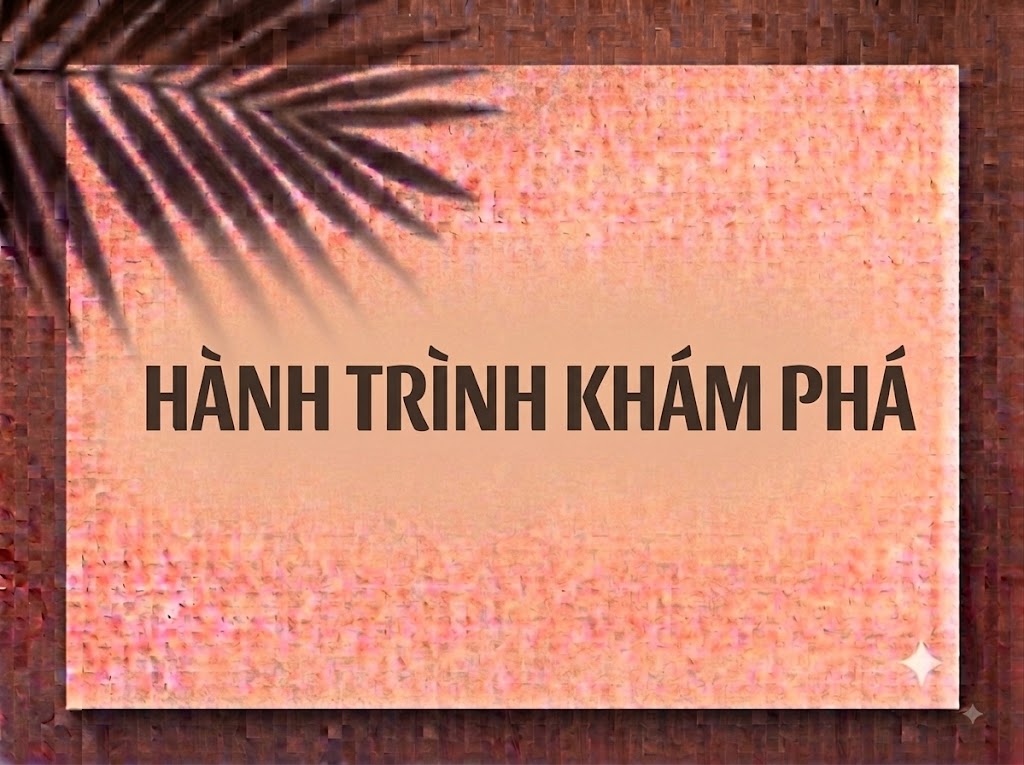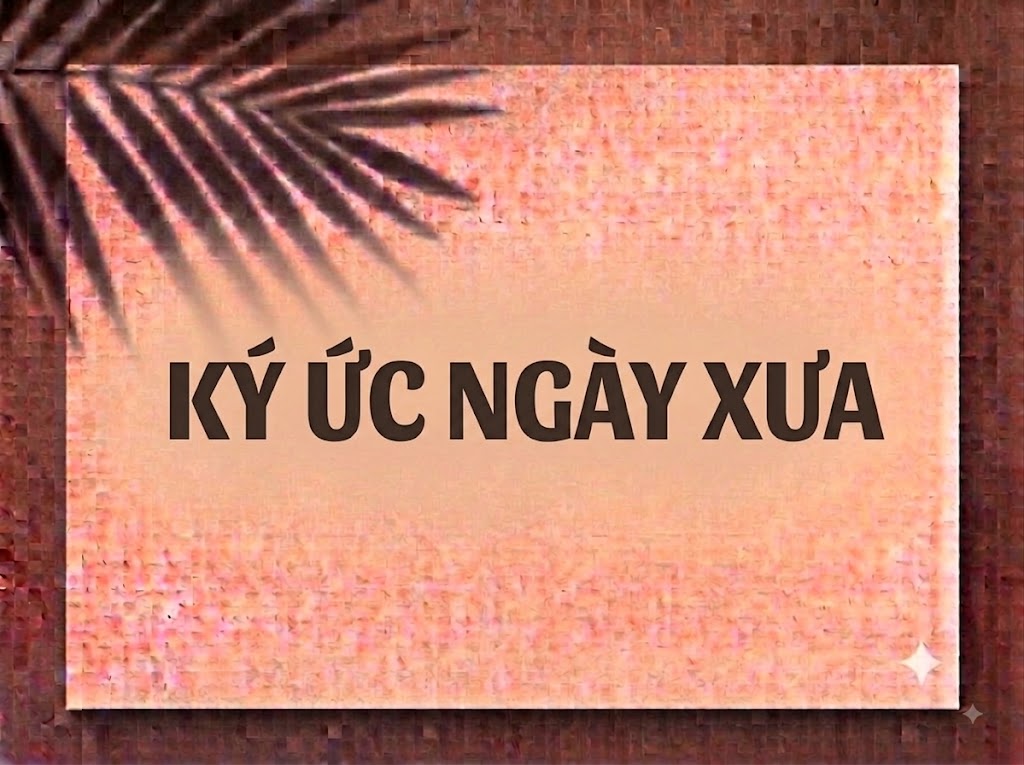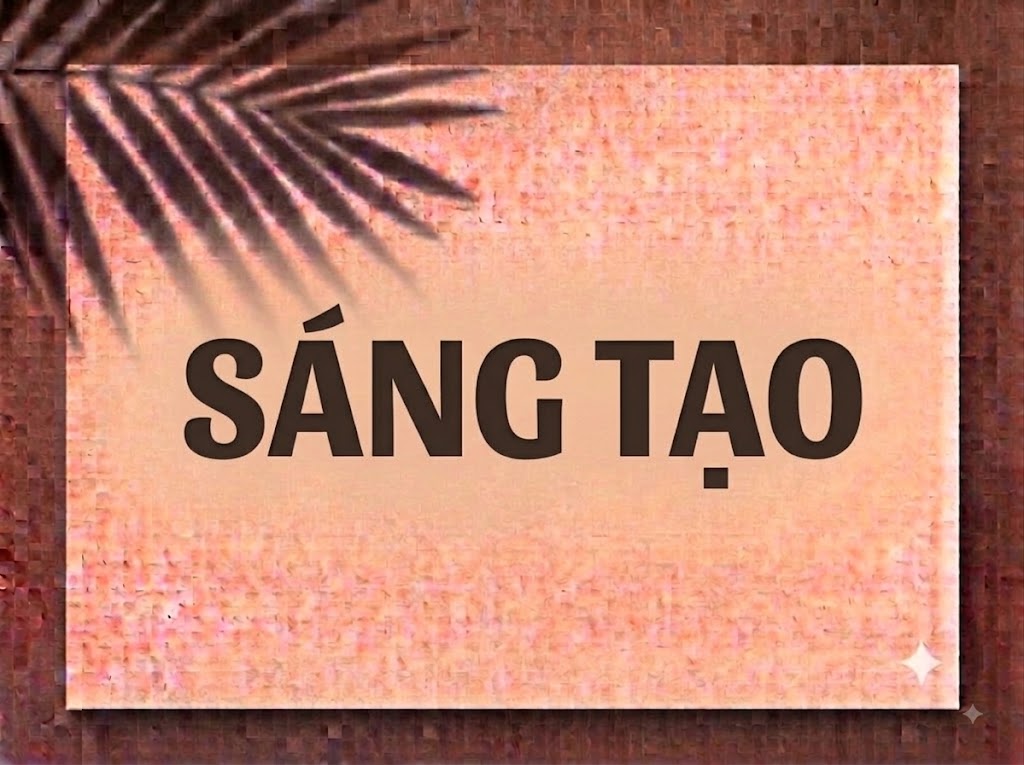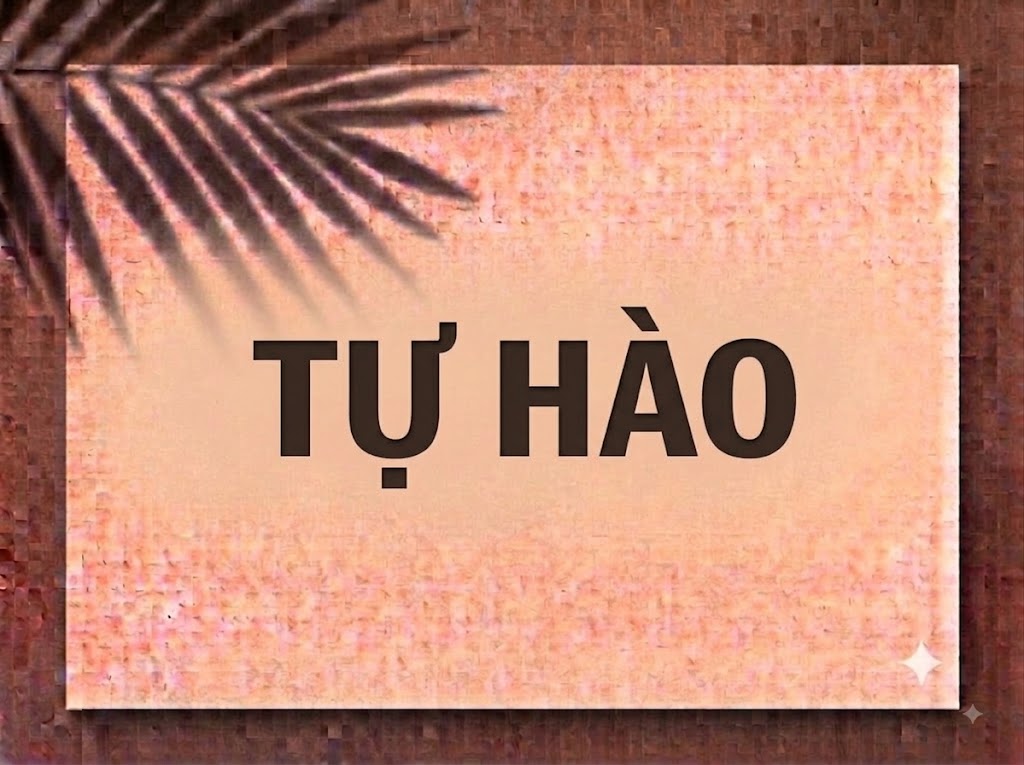
Trong thiết kế đồ họa hiện đại, đặc biệt là các lĩnh vực thể thao, eSports, công nghệ và thời trang đường phố (streetwear), những kiểu chữ Sans-Serif dáng mở rộng chiều ngang (extended/expanded) luôn tạo nên uy lực thị giác vượt trội. Với diện tích phủ nét lớn, cấu trúc hình khối vững chãi và tinh thần bứt phá, dòng chữ này giúp câu tiêu đề trở nên cực kỳ nổi bật và tràn đầy năng lượng.
Nếu bạn đang tìm kiếm một phông chữ nét đậm, dáng rộng hầm hố để làm tiêu đề banner, thumbnail YouTube, logo hay video ngắn, font 1FTV VIP Besides chính là sự lựa chọn không thể bỏ qua.
Giới thiệu về font 1FTV VIP Besides
Font 1FTV VIP Besides là bộ chữ hiển thị không chân (sans-serif display) sở hữu cấu trúc dãn ngang ấn tượng, mang phong cách hình học hiện đại và đậm chất kỹ thuật số:
Nhờ nền tảng kỹ thuật chỉn chu, phông chữ đem lại khả năng hiển thị vô cùng mượt mà trên mọi độ phân giải. Bạn có thể tự tin phóng lớn chữ trên các phần mềm thiết kế đồ họa chuyên nghiệp hay ứng dụng dựng video mà không lo bị vỡ nét hay răng cưa.
Đặc điểm nổi bật của phong cách thiết kế VIP Besides
Sức hút thị giác của font 1FTV VIP Besides đến từ phom dáng dãn rộng bề ngang cùng mảng khối cực kỳ chắc chắn:
Phom dáng Extended ấn tượng: Chiều ngang của ký tự được mở rộng tối đa, tạo cảm giác bề thế, vững chãi và đầy sức mạnh cho các câu slogan hay tiêu đề chính.
Độ dày nét Heavy/Bold cực đại: Sự kết hợp giữa nét đậm dầy và các đường cắt góc vuông vắn giúp phông chữ thu hút ánh nhìn lập tức từ khoảng cách xa.
Hỗ trợ đồng bộ chữ hoa và chữ thường: Bộ ký tự chữ hoa lẫn chữ thường đều giữ vững nhịp điệu dãn ngang đồng nhất, giúp bạn linh hoạt phối hợp để tạo nên các khối chữ tiêu đề chặt chẽ.
Khoảng cách giữa các chữ (kerning) dãn ngang và độ giãn dòng được tính toán chuẩn xác, giúp các mảng chữ lớn khi đứng gần nhau không bị dính nét hay rối thị giác.
Tích hợp trọn vẹn bộ chữ cái hoa – thường, dãy chữ số 0-9 phom khối hầm hố cùng hệ thống ký tự đặc biệt, dấu câu thông dụng.
Bản Việt hóa chuẩn chỉnh giúp bạn hoàn toàn yên tâm thiết kế các văn bản tiếng Việt có dấu mà không gặp lỗi nhảy font hay mất ký tự.
Hình ảnh demo thực tế của font 1FTV VIP Besides
Khả năng hiển thị của phông chữ này được tối ưu rất tốt trên nhiều tỷ lệ kích thước khác nhau:
Kích thước nhỏ (12pt – 24pt): Cấu trúc chữ rộng ngang và nét đậm giúp các câu chữ ngắn vẫn hiển thị rõ ràng trên các giao diện màn hình di động.
Kích thước lớn (36pt – 72pt): Đây là đất diễn lý tưởng nhất để 1FTV VIP Besides phô diễn toàn bộ sự bứt phá, hầm hố và phom dáng Extended hiện đại, tạo tác động thị giác cực mạnh cho các dòng headline.
Ứng dụng trong thiết kế đồ họa và làm video
Sở hữu nét cá tính hầm hố và giàu năng lượng, font 1FTV VIP Besides mở ra không gian ứng dụng phong phú:
Video ngắn (TikTok, Reels, Shorts): Dáng chữ mở rộng cực kỳ bắt mắt trên khung hình đứng tỷ lệ 9:16, giúp câu giật tít thu hút người xem dừng lướt feed ngay từ giây đầu tiên.
Ảnh thu nhỏ YouTube (Thumbnail): Lựa chọn hàng đầu cho các kênh về gaming, eSports, xe độ, review công nghệ, gym fitness hay nhạc EDM/Hip-hop nhờ độ nhận diện trực diện.
Banner Quảng cáo & Poster Sự kiện: Hoàn hảo cho các poster giải đấu game, sự kiện âm nhạc, chương trình khuyến mãi e-commerce hay các dự án truyền thông sôi động.
Nhận diện thương hiệu Streetwear & Tech: Thích hợp làm logo dạng chữ khối, bao bì sản phẩm hoặc in ấn thiết kế artwork trên áo thun cho các thương hiệu cá tính.